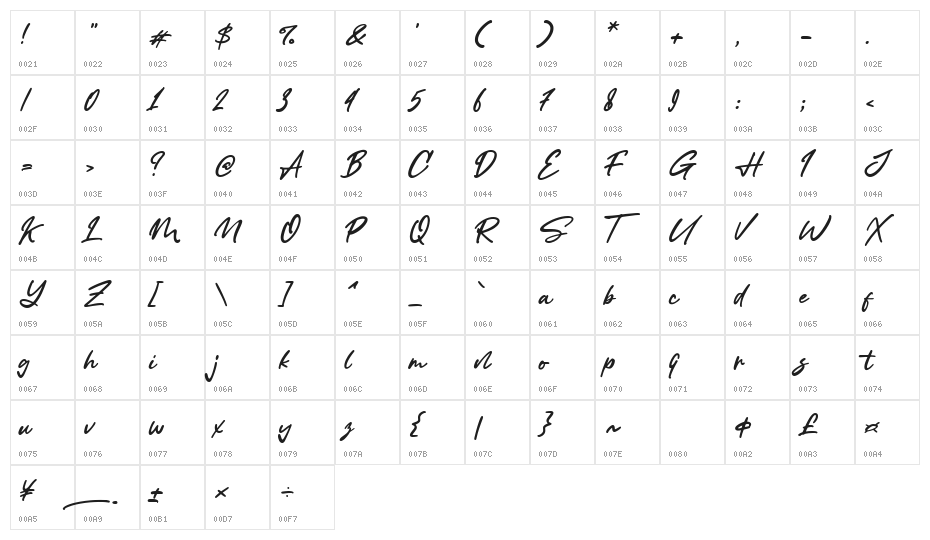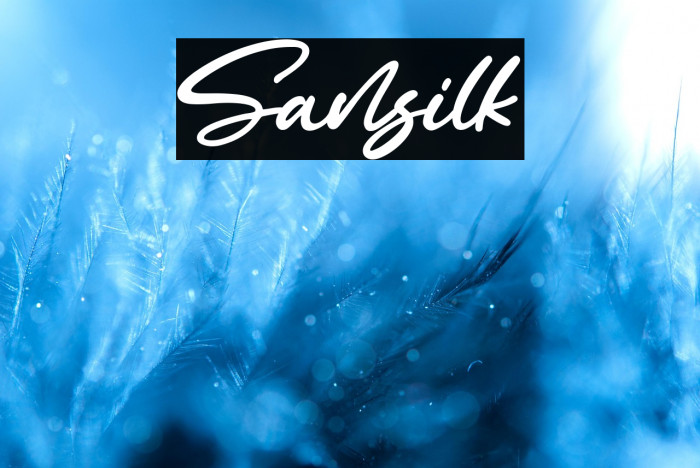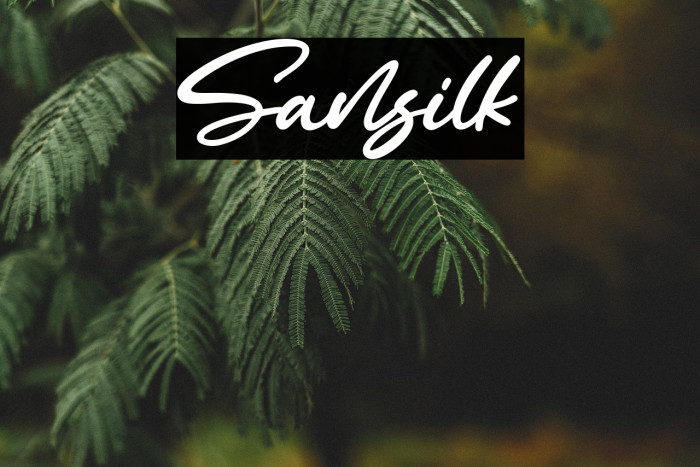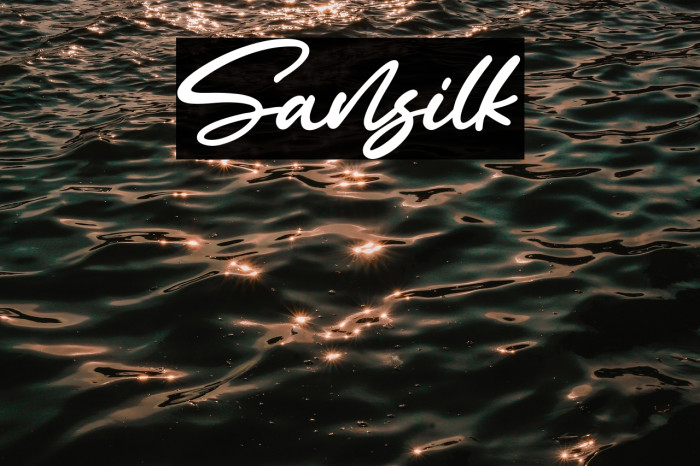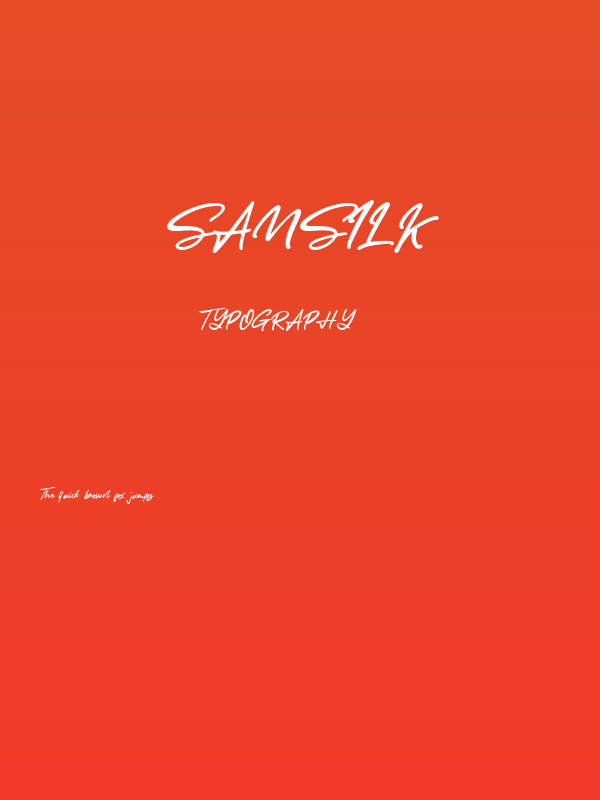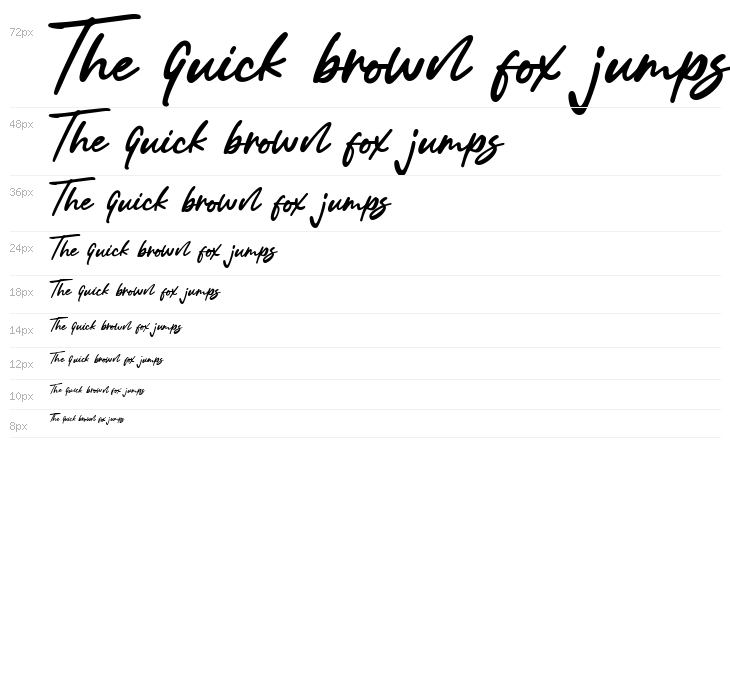
Sansilk Font
| Caz de utilizare | Logos, Invitations, Personal Branding |
| Proiecte propuse | Ideal for wedding invitations, greeting cards, personal branding, and creative projects that require a personal touch. |